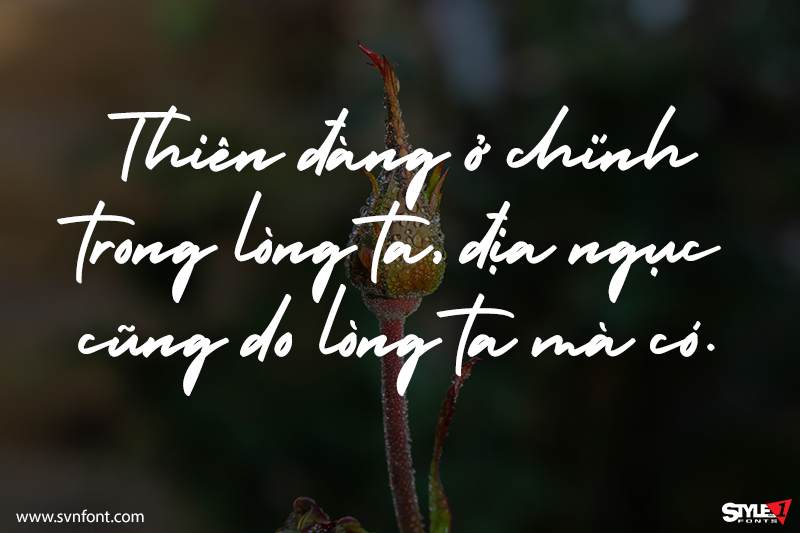
[SVN Việt hóa] Holiday - Font chữ ký đậm và sang trọng
Holiday - Bold Signature Font là phông chữ viết tay với phong cách đơn giản và sang trọng, phông chữ này rất phù hợp cho các dự án sáng tạo tiếp theo của bạn như watermark về nhiếp ảnh, thiết kế logo chữ ký hoặc chữ ký, quảng cáo, bìa album, danh thiếp và nhiều thiết kế khác dự án.
Nhà thiết kế: alphart